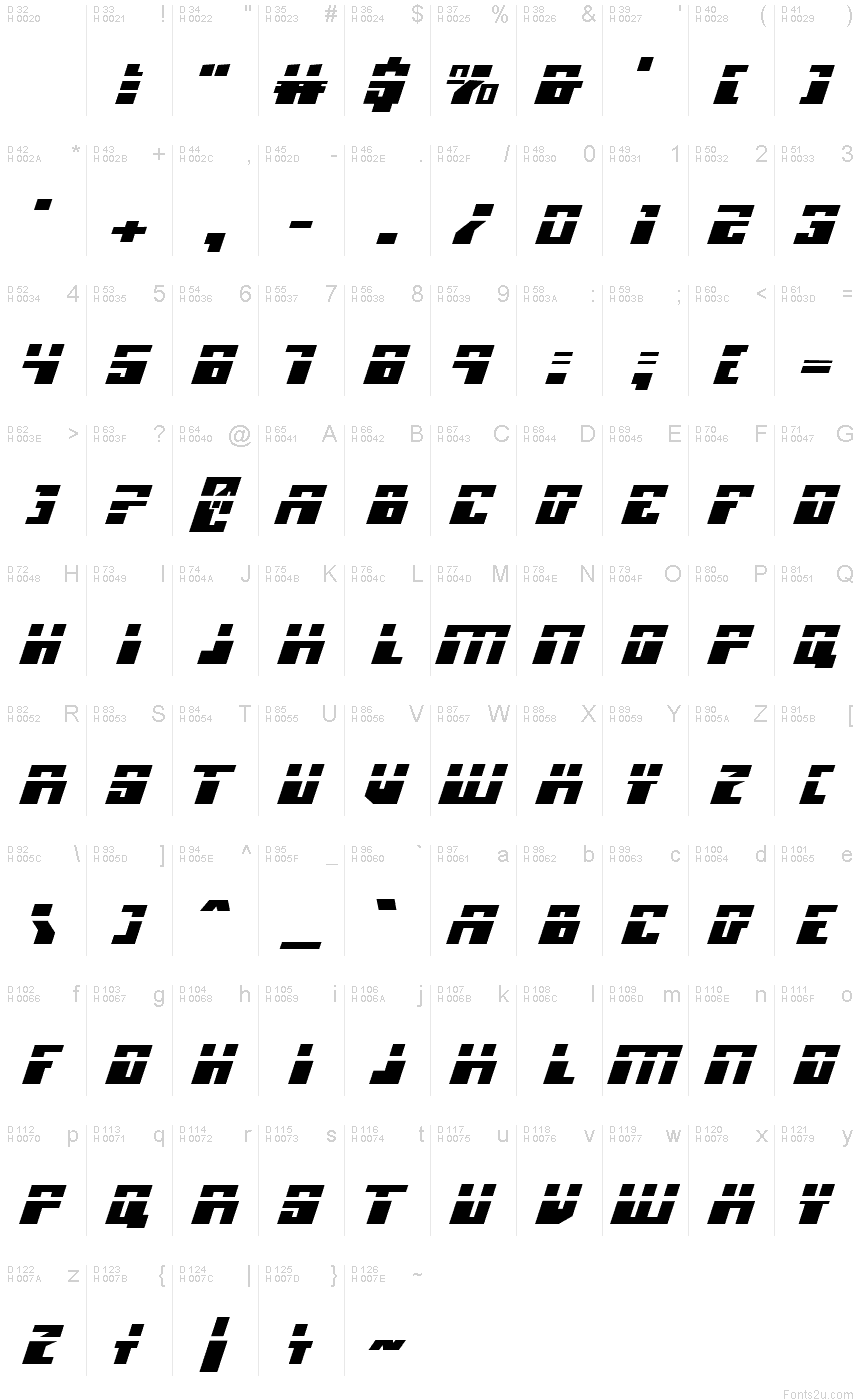
Micronian Laser Italic von Iconian Fonts ist eine kostenlose, futuristische Display-Schrift, die aus breiten, stark geneigten Strichen aufgebaut ist. Horizontale Schnitte durchziehen die Buchstaben.
Technologie und Science-Fiction sind das naheliegendste Terrain für ihre schnellen, maschinellen Formen, weshalb sie sich gut für Spielegrafiken und Artwork im Bereich der elektronischen Musik eignet. Die dichte Silhouette und die Aussparungen können zudem Produktverpackungen oder Event-Poster in etwas verwandeln, das an Rennsport-Aufkleber, Raumschiff-Markierungen oder digitale Benutzeroberflächen erinnert. Ihr stärkstes Publikum sind wahrscheinlich Designer in den Bereichen Gaming, Motorsport, Clubkultur und anderen Unterhaltungsbranchen, die eine Vorliebe für aggressive, industrielle Schriften haben.
Micronian Laser Italic